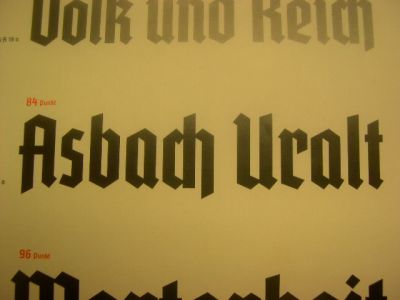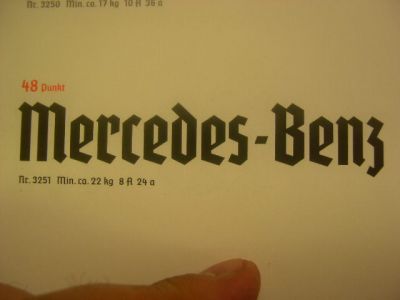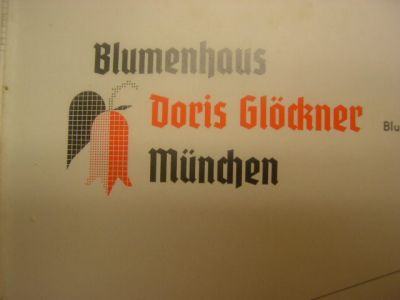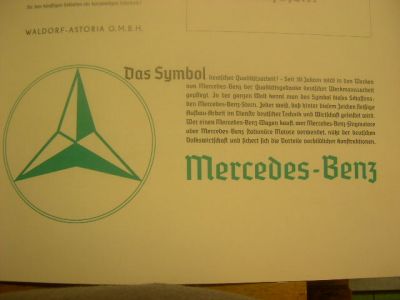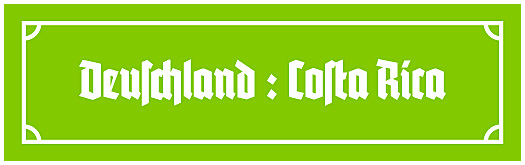
Georg, ich bin grundsätzlich auch gegen eine Aufsplitterung der Diskussion, denn gerade durch das unerwartet-unkontrollierte Mäandern entstehen ja die interessanten neuen Wendungen. Ich finde nur, dass wenn wir von der Tannenbergschlacht zur modernen Frakturanwendung und zurück hüpfen, unnötige Wiederholungen und Umwege nehmen. Es gibt kein «eigentliches Thema», das ist mir schon klar.
Meine Meinung zu Deinem «Grundproblem» (Bleisetzer) in ein paar Sätzen? Ich finde es irgendwie rührend: Heute beginnt die WM, die ganze Welt gönnt Deutschland ihr neu gefundenes Nationalgefühl von Herzen. Die ganze Feuilletonwelt diskutiert über Matusseks «Wir Deutschen». Deutschland wird von rundherum zugebilligt, unverkrampfter zu ihrem Land zu stehen. Die ganze Welt sieht in den nächsten Wochen Meere von Deutschlandfahnen und fröhlichen Deutschen. – Und irgendwo sitzt ein einsamer Bleisetzer, der grimmig durch die Zähne zischt: «Und warum darf ich meine Preußenflagge nicht auf den Balkon hängen? Wegen der amerikanischen Propaganda, jawoll.»
Unterstellung.
Noch einmal: Ich habe keinerlei missionarische Ambitionen in Bezug auf Preußen und auch nicht die Illision, daß es jemals wieder ein Deutschland im preußischen Sinne geben wird.
Behauptung:
Ich weiß, warum Ihr Euch beim Denken im Kreis bewegt.
Es ist ein gedankliches Problem, das Ihr habt, nicht eines mit Eurer politischen Anschauung. Ihr verwechselt ganz einfach was. Wegen Eurer Konditionierung.
Niklaus, das war ein Missverständnis.
Immer geht das schief mit der Ironie ... :evil:
Natürlich bezieht sich der Name der Schrift auf
den Sieg im ersten Weltkrieg. Meine historische
Zusammenfassung war ein ironischer Reflex auf
Georgs Beitrag:
Einen Rückschluß nun auf eine spätere Interpretation zu reduzieren und diese so praktisch losgelöst aus dem historischen Zusammenhang zu werten, halte ich eher für Sophisterei.
Und es klärt sich ja auch schon wieder etwas.
Wenn die Tannenberg 1929 entstanden ist, kann sich die
Benamung der Schrift nicht auf die Hindenburg-Beisetzung
beziehen, da lebte der Mann ja noch. Das Denkmal gab es schon,
und es gab auch schon die Einbettung der Schlacht (die wurde
gewonnen, der Krieg bekanntlich nicht) in die Dolchstoß-Legende
(im Felde unbesiegt).
Also: niemand bezweifelt, dass die Deutschen die Russen bei
Allenstein/Grunwald/Possenheim/Hohenstein/Frankenau/Tannenberg
im Jahre 1914 besiegt haben.
Niemand bezweifelt, dass der Sieg der Deutschen über die Russen bei
Allenstein/Grunwald/Possenheim/Hohenstein/Frankenau/Tannenberg
im Jahre 1914 eher überraschend war.
Und damit hat sichs. Eine weitere Diskussion militärischer Details
verbietet sich hier. Wir sind in einem Typografie-Forum.
Als die Schrift geschaffen wurde, war der erste Weltkrieg 11 Jahre
vorbei. Was kann man über diese Zeit sagen? Uns interessiert,
warum der Name eines Ortes, in dessen Nähe ein bis zwei Schlachten
stattgefunden haben, für eine Schrift Verwendung findet.
Ja, das mit der Ironie ist so eine Sache, das schrieb schon Tucholsky.
Euer Problem ist:
These:
Ihr werft alles in einen Topf:
Nationalsozialismus, nationales Denken, Patriotismus, Nationalismus, Diktatur, Chauvinismus, Imperialismus. Alles das rührt ihr zusammen und nennt es Nazi-Kram. Und dann greift der Abscheu-Reflex. Wem auch immer es gelingt, ein Thema in den Topf Nazi-Kram mit einzuschmuggeln, hat gewonnen: Euer Reflex funktioniert.
Bestes Beispiel: Tannenberg, erste Entwürfe 1929. Erstguß 1934.
Reflex: Machtergreifung der Nazis 1933, ergo: Nazi-Schrift.
Steht nicht drauf? Macht nichts. Wird "heutzutage von allen so assoiziiert, vor allem im Ausland". Nazi-Schrift, basta.
Hier noch eine Schrift, die Ihr für die Visitenkarten Eurer Deutschen Förster bitte nicht verwenden dürft:
Was sich in Euren Nachkriegsköpfen abspielt, sobald es um Geschehnisse vor 1945 dreht, ist konditioniert. Was "rechts" von der CDU ist, ist Nazi-Kram. Nationalbewußtsein? Nazi-Kram. Du-bist-Deutschland? Eine Lachnummer. Weiß doch jeder: "Geiz ist geil" und "Ich bin doch nicht blöd". Und deshalb könnt Ihr als Teile einer Ich-Gesellschaft nicht verstehen, was Menschen einer Wir-Gesellschaft empfunden haben.
Natürlich war "Tannenberg" ein, heute würde man sagen: vom Marketing ausgewählter Name. Und er sprach genau das Gefühl der Nutzer an und die Schrift war sehr erfolgreich. Nicht, weil die Förster, die sich beim Drucker die Tannenberg wünschten, Nazis waren. Und auch nicht die Drucker selbst, die die Tannenberg empfahlen. Sondern weil diese Schrift, verstärkt durch ihren Namen, das Werte- und positive Nationalgefühl aller dieser Menschen ansprach.
Das ist Euch heute fremd. Und das ist logisch sehr einfach nachvollziehbar.
Wenn Ihr aber eine Schrift aus dieser Epoche verstehen wollt, dann könnt Ihr nicht von Eurem heutigen Bewußtsein ausgehen, sondern müßt die Schrift aus der damaligen Zeit heraus bewerten.
Die Passagen in Susanne Wehdes «Typographische Kultur» gehören für mich zum Informativsten, das es zum ‹Frakturstreit› gibt. Bei so viel Quatsch, das zum Thema geschrieben wurde, sollte der Text eigentlich zur Pflichtlektüre für alle hier Diskutierenden sein, es würde viel Leerlauf ersparen.
In dem – leider etwas flüchtig-impressionistisch hingepinselten – Büchlein «Die Schwabacher» (2003) von Philipp Luidl wird übrigens insinuiert, dass der Gegensatz Antiqua–Fraktur die Vorlieben Hitlers (Antiqua) bzw. Heinrich Himmlers (Fraktur) spiegle.